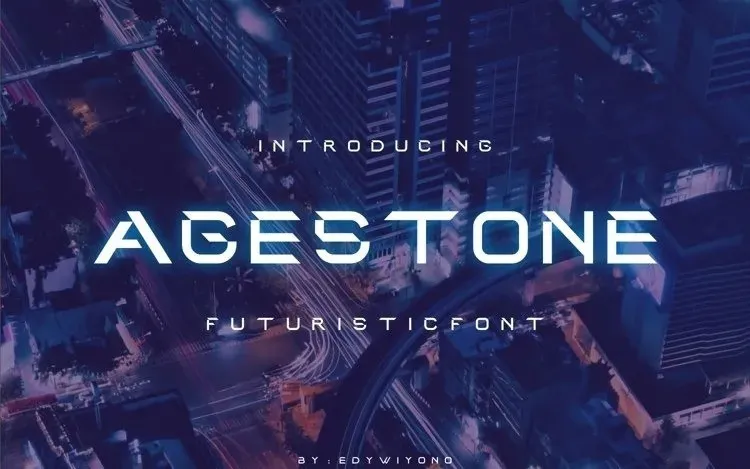
A Agestoned Font é uma elegante escolha para ambientes visuais modernos e futuristas. Composta inteiramente em letras maiúsculas e apresentando um aspecto limpo e não sofisticado, a fonte foi criada pelo designer edywiyonopp através de 99designs. Esta tipografia é ideal para aplicação em sites, revistas e logomarcas que buscam uma concepção moderna, masculina e futurista. Seja você um criador digital ou profissional do design gráfico, Agestoned é perfeito para trazer personalidade e distinção a seus projetos visuais.